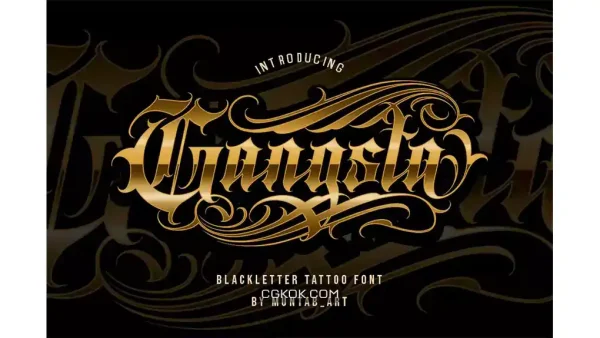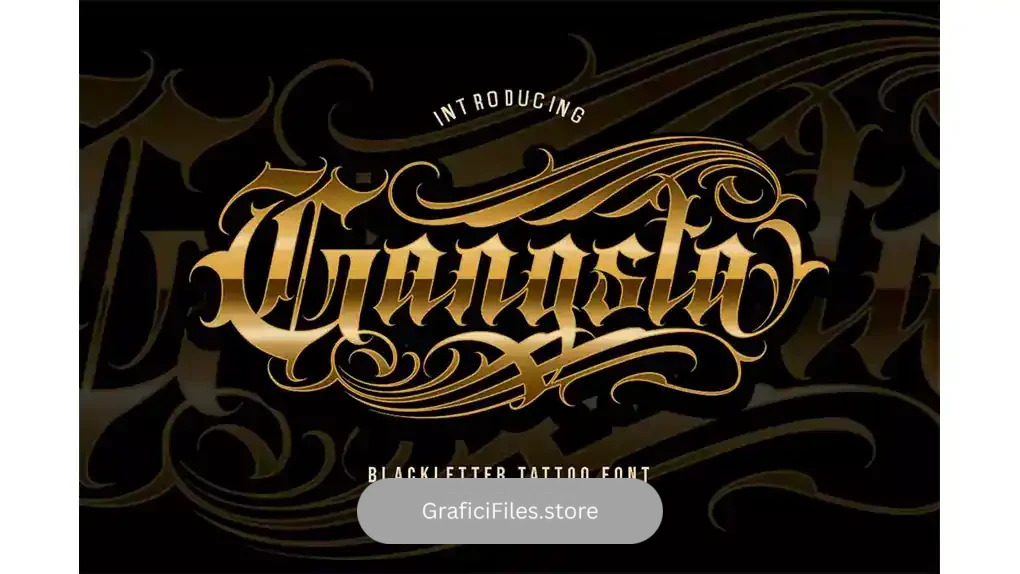
فونت انگلیسی تاتو Gangsta Typeface | Tattoo Fonts : این مجموعه شامل یک فونت انگلیسی کلاسیک است که برای تاتو، برندینگ، لوگو، تیشرت، پوستر و غیره مناسب میباشد.
• فضا بین حروف: معمولی